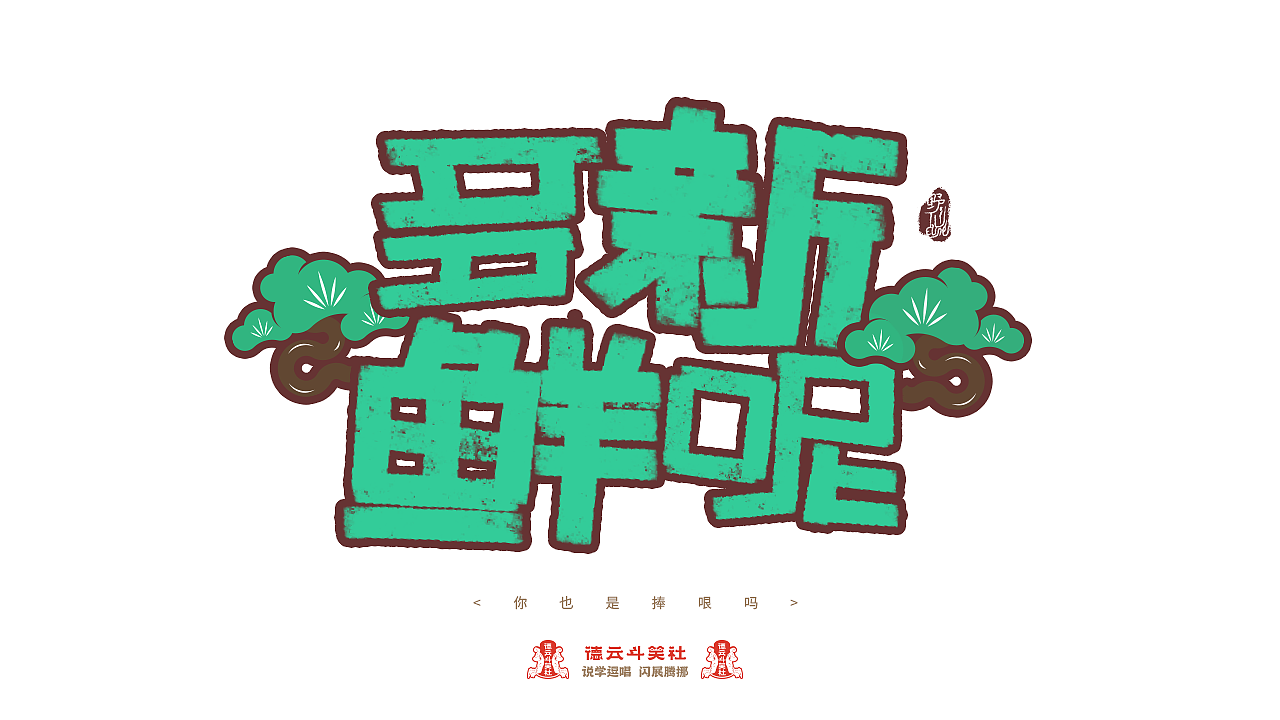
德云斗笑色 捧哏词牌创意 POP风格手写
德云斗笑色 捧哏词牌创意 POP风格手写(图ZMjc0OTcyOTY4) - 字体/字形 - 站酷设计师野仙ELSIE原创素材 - 站酷ZCOOL
德云斗笑色 捧哏词牌创意 POP风格手写(图ZMjc0OTcyOTY0) - 字体/字形 - 站酷设计师野仙ELSIE原创素材 - 站酷ZCOOL
德云斗笑色 捧哏词牌创意 POP风格手写(图ZMjc0OTcyOTYw) - 字体/字形 - 站酷设计师野仙ELSIE原创素材 - 站酷ZCOOL
德云斗笑色 捧哏词牌创意 POP风格手写(图ZMjc0OTcyOTcy) - 字体/字形 - 站酷设计师野仙ELSIE原创素材 - 站酷ZCOOL
德云斗笑色 捧哏词牌创意 POP风格手写(图ZMjc0OTcyOTgw) - 字体/字形 - 站酷设计师野仙ELSIE原创素材 - 站酷ZCOOL
德云斗笑色 捧哏词牌创意 POP风格手写(图ZMjc0OTcyOTc2) - 字体/字形 - 站酷设计师野仙ELSIE原创素材 - 站酷ZCOOL